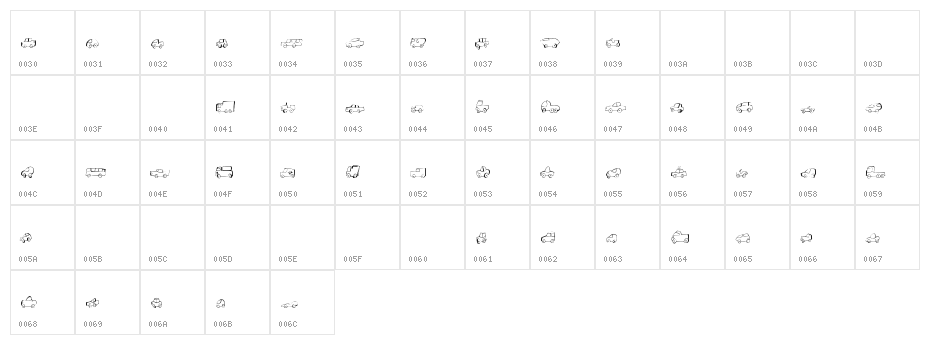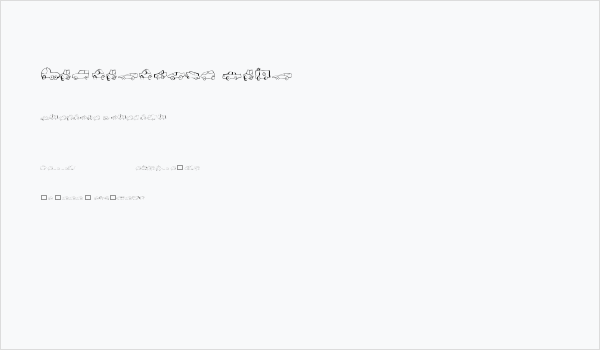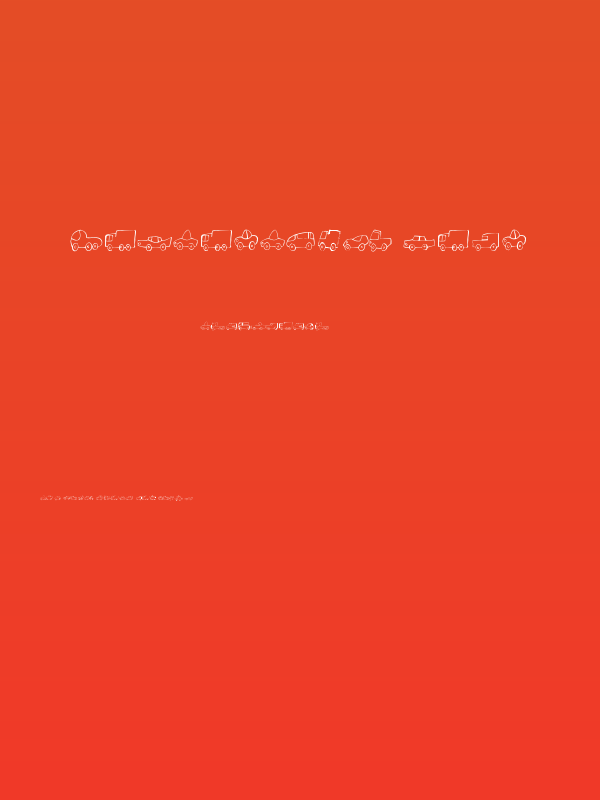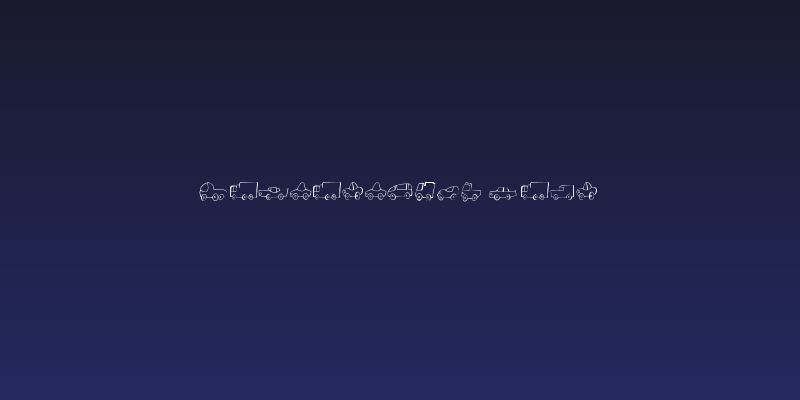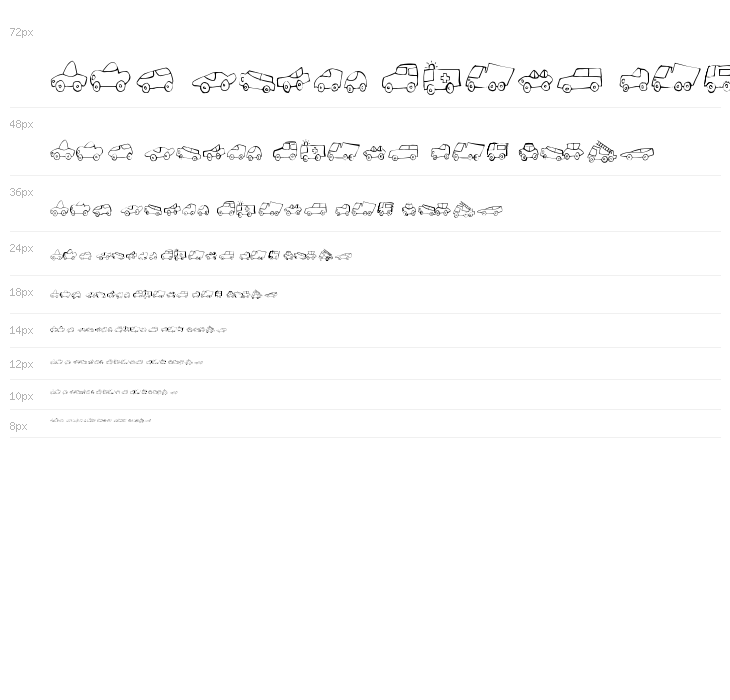
Fantastique Cars Font
| Caso d'uso | Logos, Posters, Creative projects |
| Progetti proposti | Ideal for children's books, playful posters, automotive-themed invitations, or any project requiring a fun and imaginative touch. |